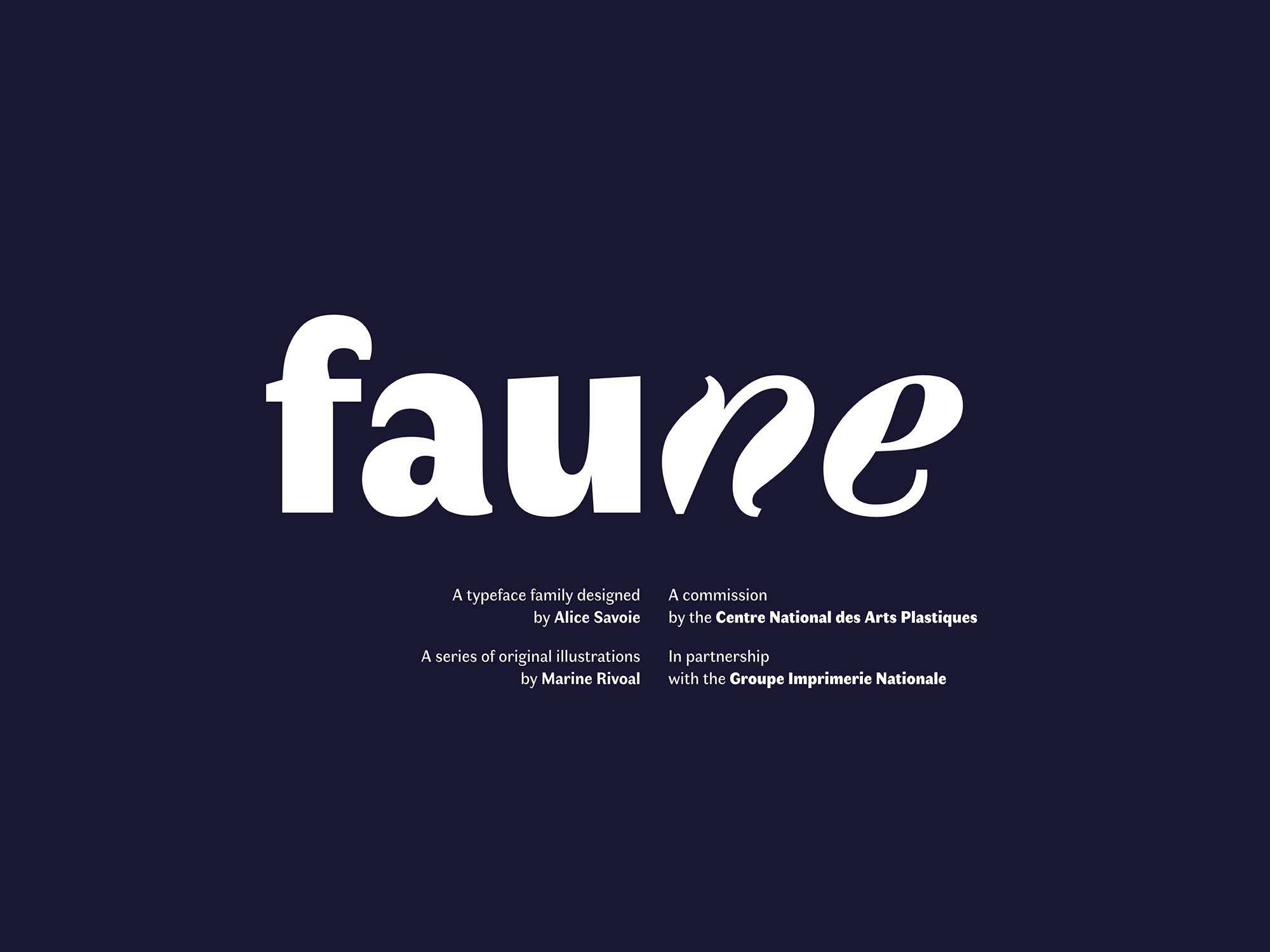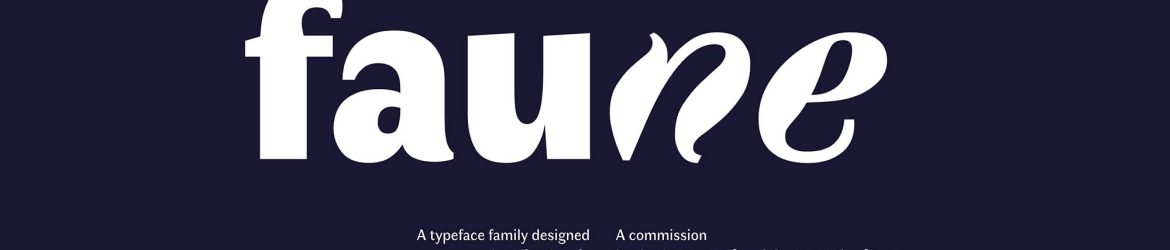
Faune Free Font é um recurso gráfico de alta qualidade que retrata a delicadeza e a elegância de uma fonte criada pela ilustradora Alice Savoie, a pedido do Centre National des Arts Plastiques. Este tipo de letra é contemporânea e transmite a leveza e a fluididade da natureza e da vida através de linhas suaves que fluem de maneira romântica e natural. A Faune é um exemplar perfeito da dinâmica da vida e do ecossistema natural, com as inclinações e curvas que fluem e se sobrepõem em harmonia. A fonte é ideal tanto para aplicar em textos suaves que representam a onda gentil quanto para textos em negrito que destacam a força, oferecendo uma ampla gama de possibilidades criativas para seus projetos. Faune Free Font é uma escolha inteligente para qualquer projeto que deseje incorporar o encanto romântico e a simplicidade da natureza na sua arte digital.